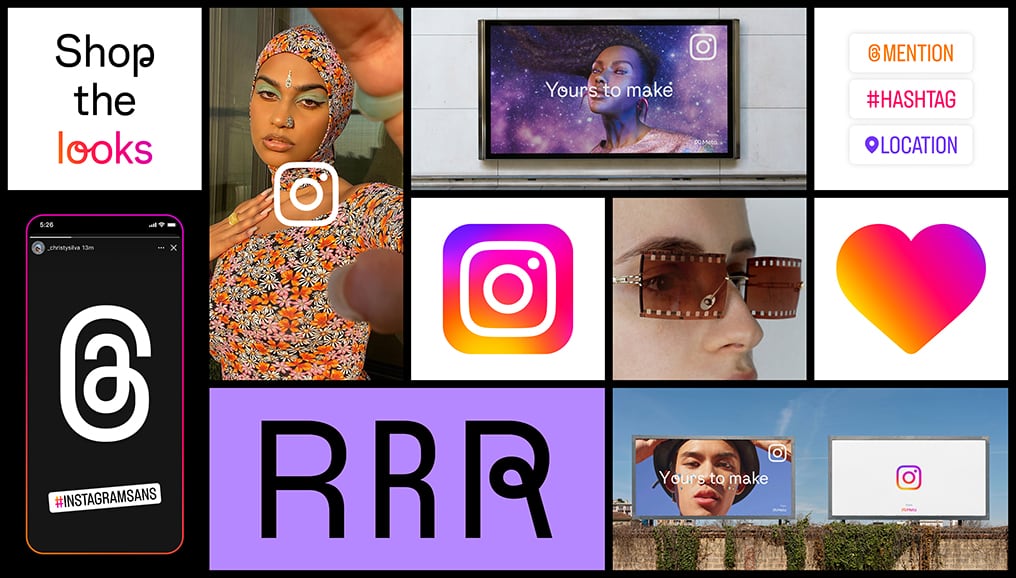
Die Plattform Instagram (App Store-Link), mittlerweile zum Zuckerberg’schen Meta-Konzern gehörend, hat mit dem heutigen Tag eine „Markenauffrischung“ durchgeführt. Dazu zählt vor allem ein visueller Neuanstrich mit aktualisierten Logos, Farbverläufen – und auch einer komplett neuen Schriftart. Letztere heißt Instagram Sans und soll in Zukunft sowohl im Marketing als auch in der App selbst Verwendung finden.
Instagram Sans wurde laut eines Blogeintrags vom Logo des sozialen Netzwerks inspiriert. So heißt es im Blog von Instagram:
„Instagram Sans ist von den Designelementen inspiriert, die unsere Community jeden Tag sieht – unser Logo und unsere Wortmarke. Von Plakatwänden bis hin zu Websites unterstreicht unsere neue Schriftart unsere unverwechselbare Identität. Auf allen Oberflächen, von unseren Marketingkampagnen bis hin zu unseren Websites, hilft Instagram Sans uns, eine klare Identität zu zeigen.“
Grundsätzlich zeigt die neue Schriftart Anleihen an eine Kombination aus Quadraten und Kreisen. Das soziale Netzwerk nennt diese „Squircles“, die für eine Verspieltheit in der Schriftart sorgen. So gibt es einige abgerundete Formen, beispielsweise bei Großbuchstaben, und auch eine Abrundung beim „t“, „h“ und mehr.
Laut Instagram war es dem Unternehmen wichtig, die Instagram Sans-Schriftart auf globaler Ebene anpassbar und zugänglich zu gestalten. Man habe sich mit Sprachexperten und -expertinnen aus der ganzen Welt zusammengetan, um die Schriftart an weltweite Skripte wie Arabisch, Thai und Japanisch anzupassen. „Wir möchten alle unsere Schöpfer und Community-Mitglieder unterstützen, die die Kultur vorantreiben und sich in jeder Sprache ihrer Wahl voll und ganz ausdrücken können“, so Instagram. Wie gefällt euch die neue Schriftart?